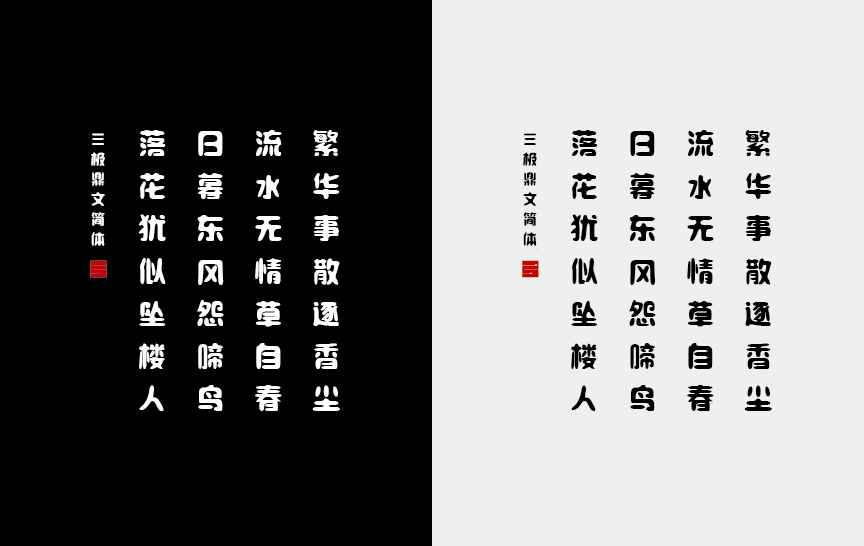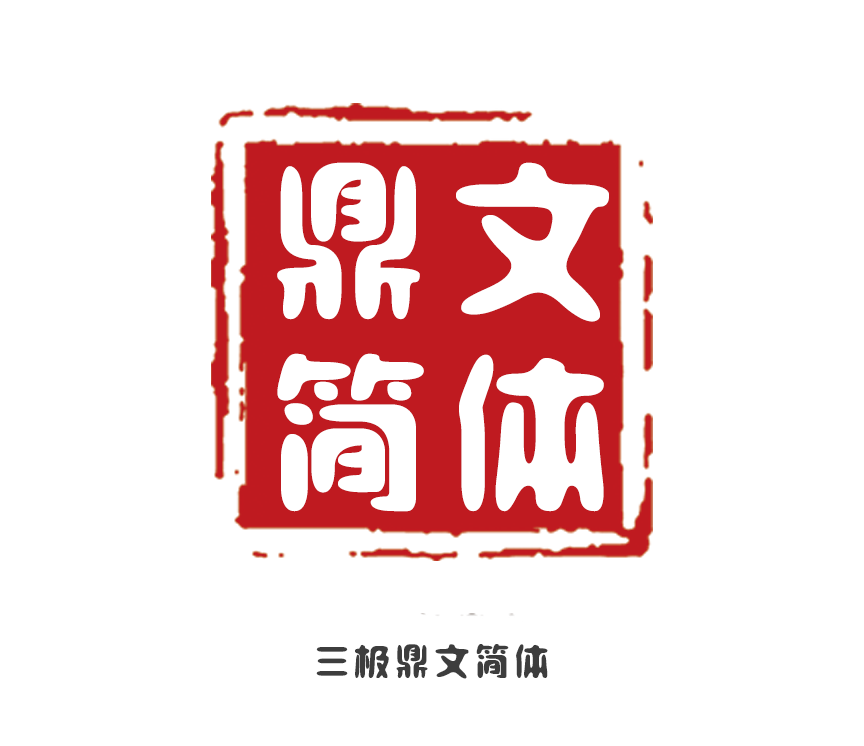
三极鼎文简体
曹陆迎
三极鼎文简体创意源自铸刻于钟鼎之上文字,笔道肥粗,弯笔多,团块多。笔画由粗细相参而趋于均匀划一;收笔与起笔为圆笔;字形端正,端整之中又有流丽之风。其以曲线为主,间架平稳,整齐中寓变化,气势奔放,特点明显。适用于少儿类读物、书刊、品牌广告、文化用品包装设计以及社交网络个性化用字。